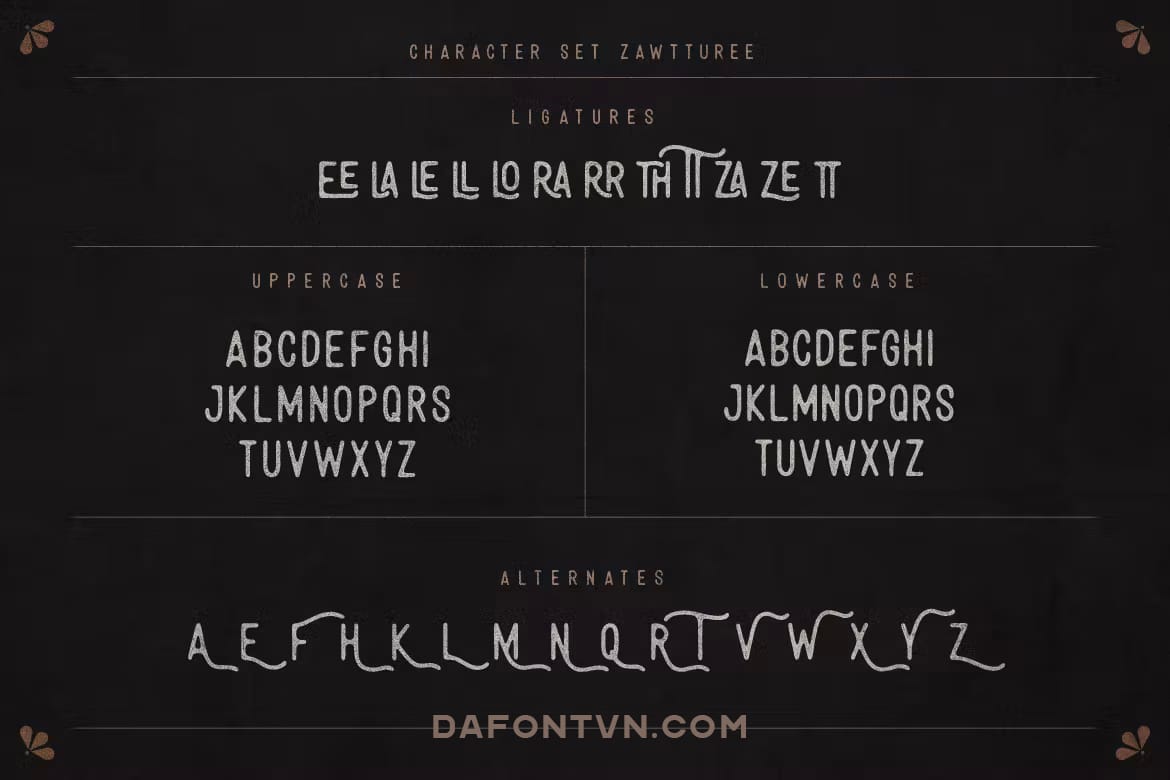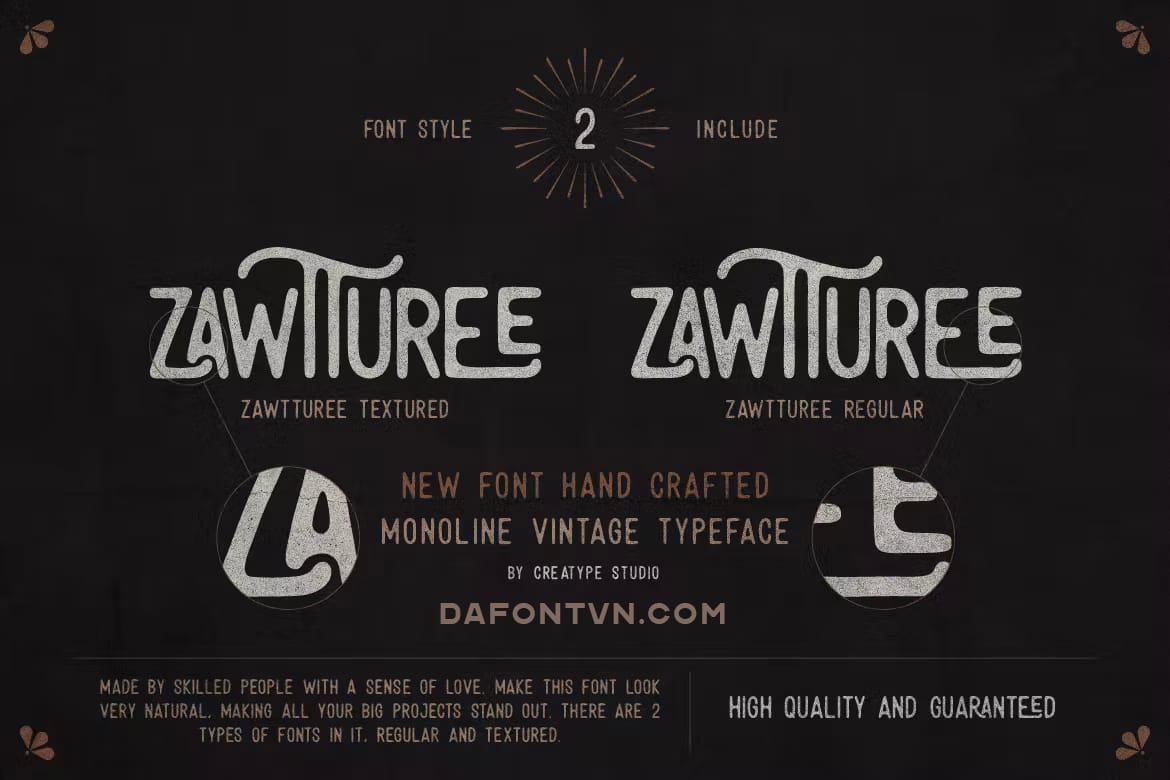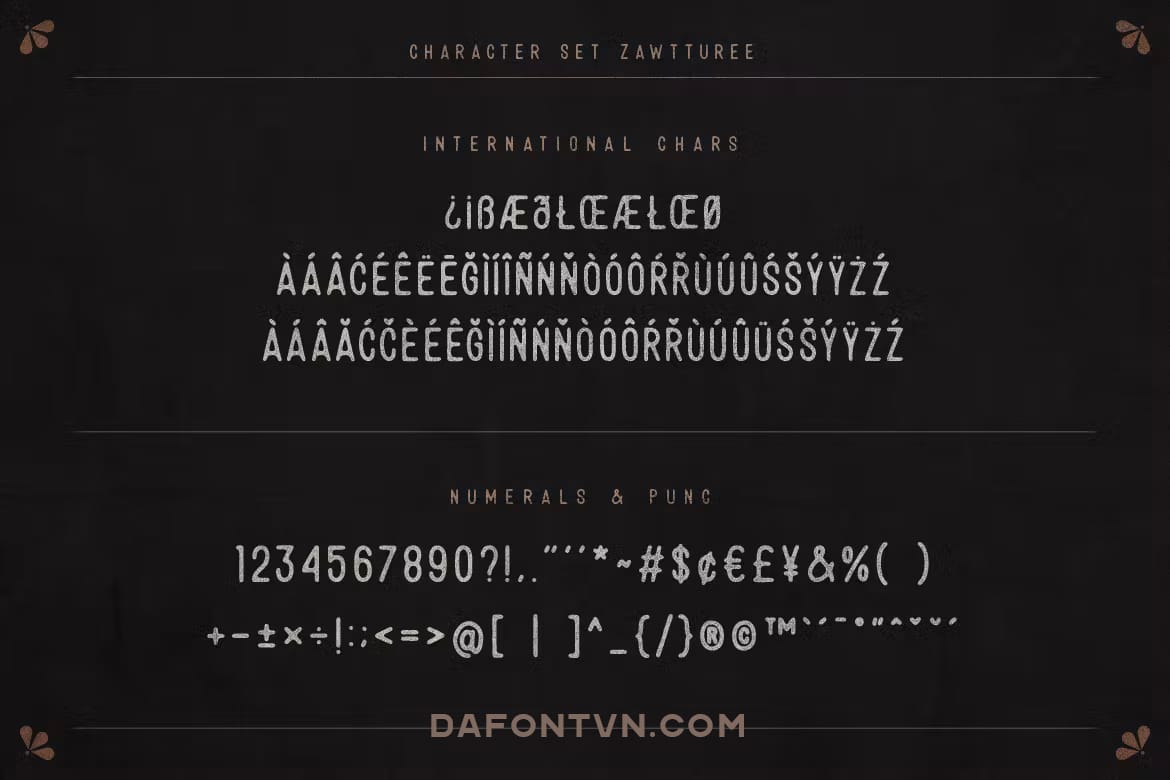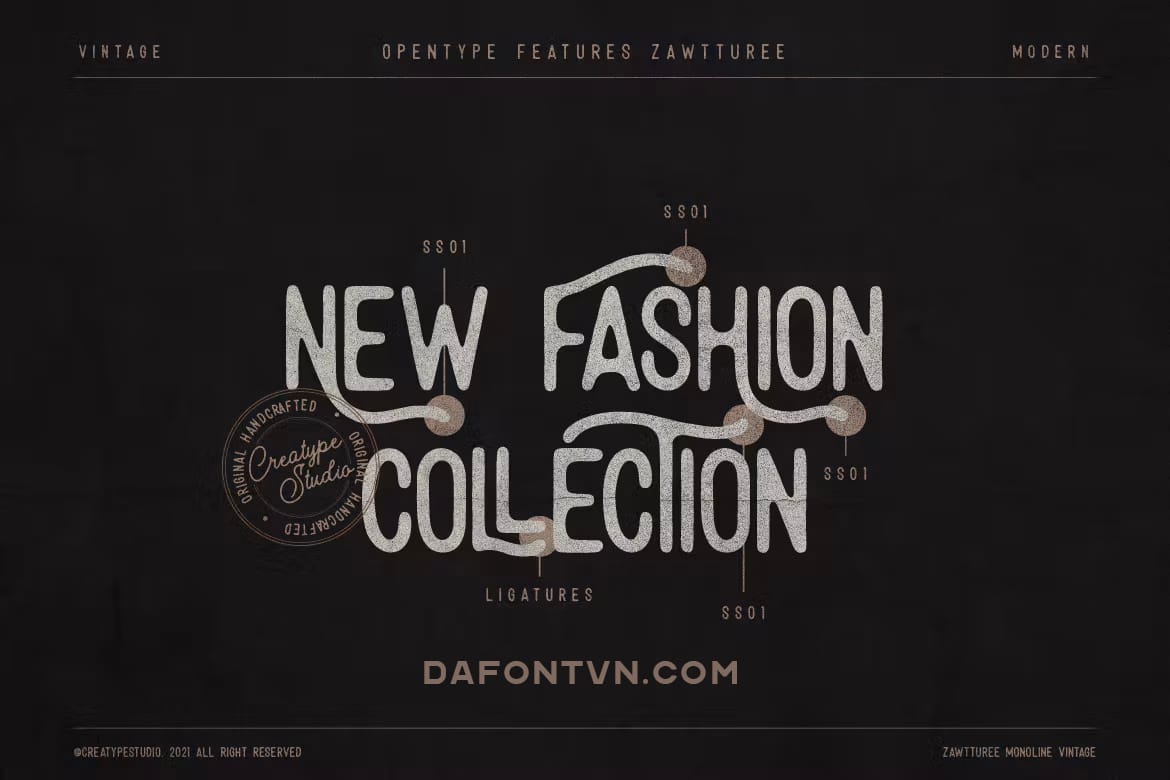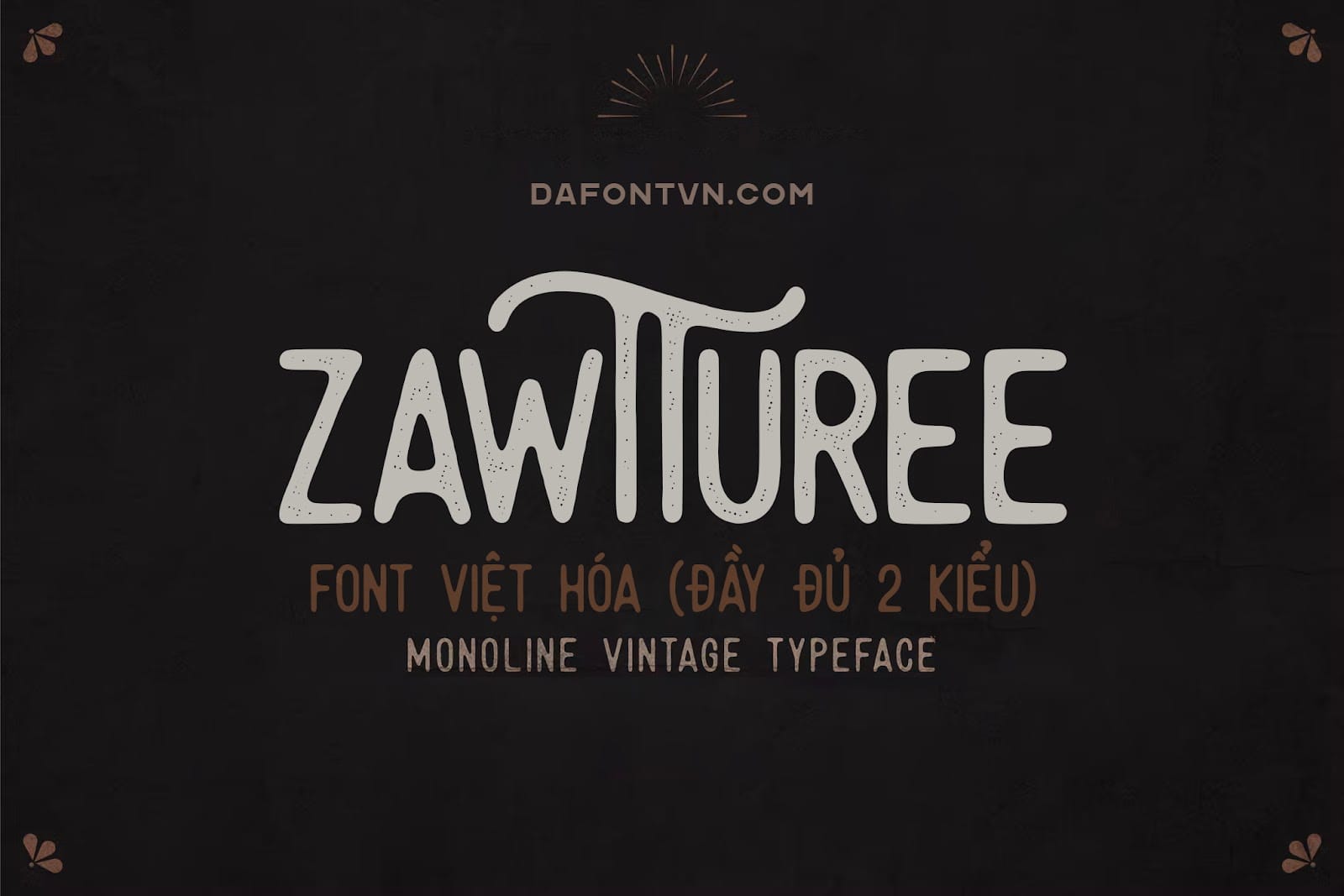
Zawturee là một font chữ cổ điển được tạo ra với cảm hứng từ những thiết kế vintage. Phông chữ rất tự nhiên với 2 kiểu đó là Regular và Textured. Font Zawturee hoàn hảo cho mọi dự án của bạn như xây dựng thương hiệu, logo, quảng cáo, thiết kế sản phẩm, thừ mời và bất kỳ dự án nào cần phong cách viết tay ấn tượng. Ngoài ra font còn bao gồm rất nhiều glyph đẹp để bạn có thể áp dụng cho các tác phẩm thiết kế của mình trở nên đặc biệt hơn.Font Zawturee việt hóa đầy đủ 2 kiểu, kerning, features, chỉnh sửa lại đôi chút các dấu và các ký tự được mã hóa PUA vì vậy bạn có thể sử dụng trên hầu hết các phần mềm thiết kế khác nhau.